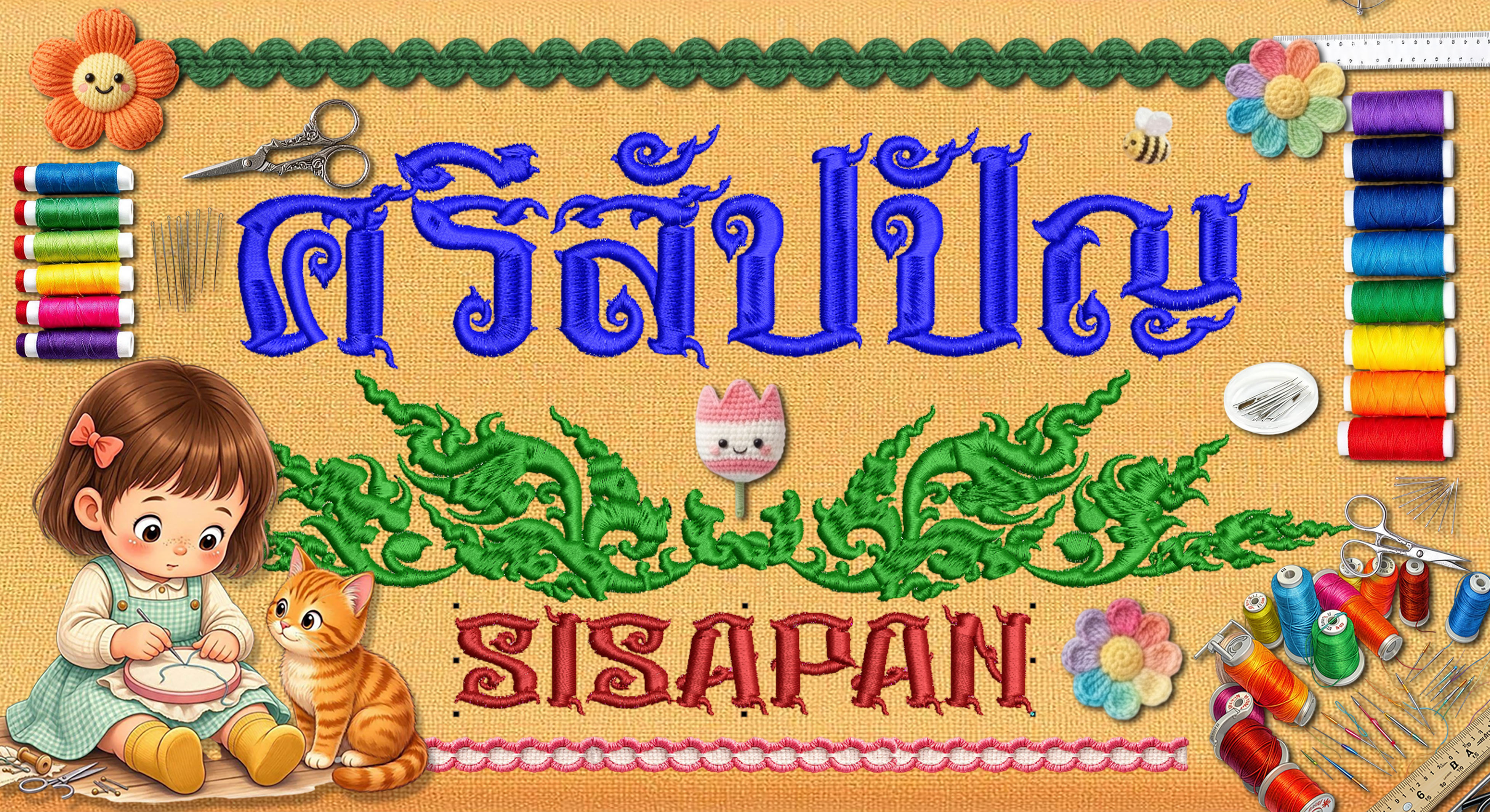
พิกัดฟอนต์ฟอนต์เบบี้ซอฟต์ (PKF-babysoft)
ฟอนต์กึ่งทางการ มินิมอล ไม่มีหัว
ฟอนต์โมยาชิ (KT-Moyashi)
- ฟอนต์ KanchaEasy ฟอนต์ลายมือแนวน่ารักเรียบร้อย อ่านง่ายสบายตาค่ะ
ฟอนต์โดนัท 🍩
ฟอนต์ลายมือเรียบร้อย อ่านง่าย สบายตา
ฟอนต์ มิกซ์ฟรุต (FH Mixed Fruit)
ลายมือสไตล์น่ารัก สดใส ขี้เล่น แต่อ่านง่าย สำหรับงานออกแบบกราฟิก แต่งภาพคอนเทนต์คาเฟ่ หรือโพสต์รีวิวก็ดูน่าสนใจ
เวอร์ชันเต็ม มี 3 น้ำหนัก
SP_Sisapan ศรีสัปปัญ
SP_Sisapan ศรีสัปปัญ เป็นฟอนต์ที่อยู่ในโครงการอักษราสูตรไทยวิจิตร เน้นการออกแบบลายเส้นให้กลมกลืนกับศิลปะลวดลายไทย
จัดรูปแบบอักษรให้เป็นเอกลักษณะเฉพาะตัว เข้ากันกับชุดอักษรนั้นๆ รวมถึงอักษรภาษาอังกฤษและสัญลักษณ์อื่นๆครบถ้วนบริบูรณ์
ชื่อฟอนต์ : ยุนอา
ฟอนต์ยุนอา ต้นทางจากโปสเตอร์หนังเรื่อง "มนต์รักอสูร" และ "ไฟรักอสูร"